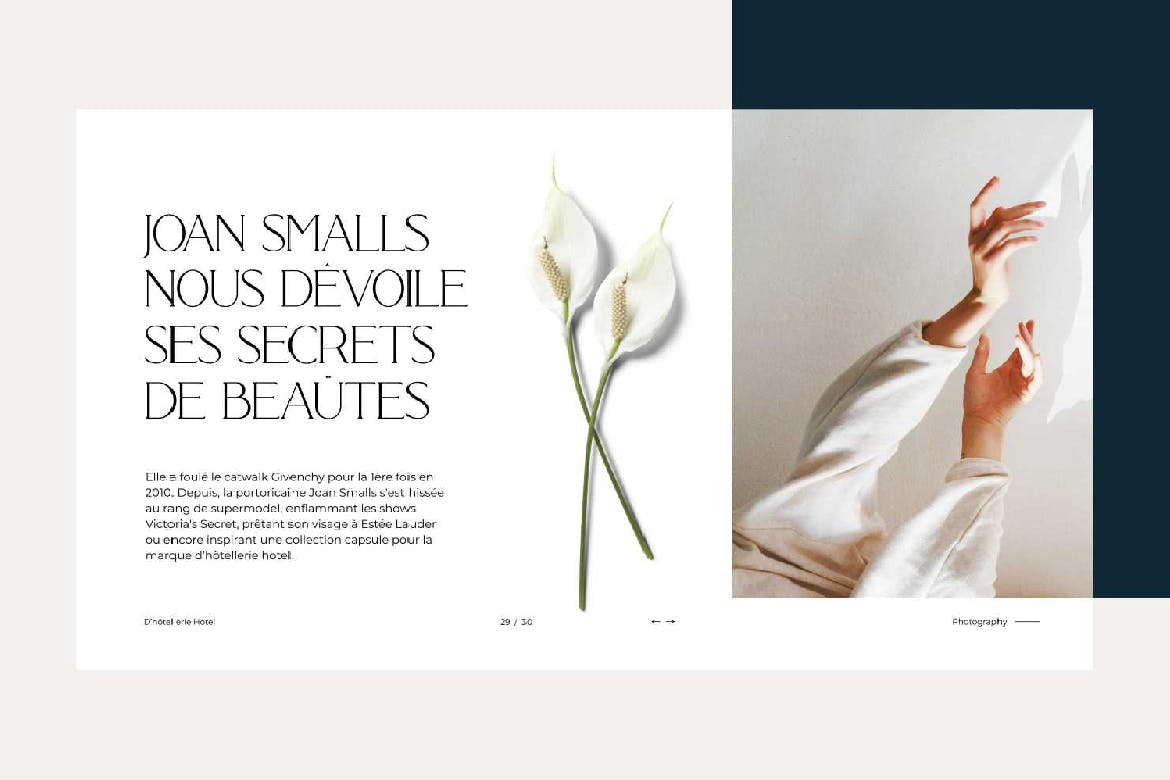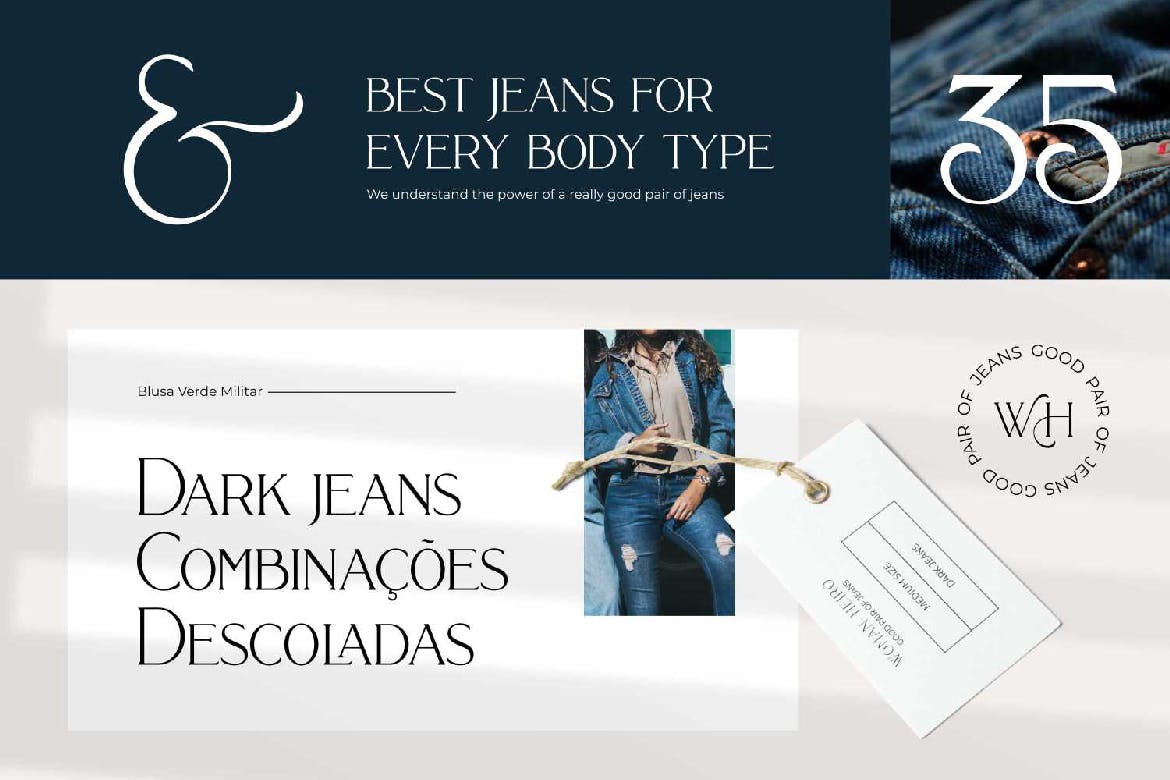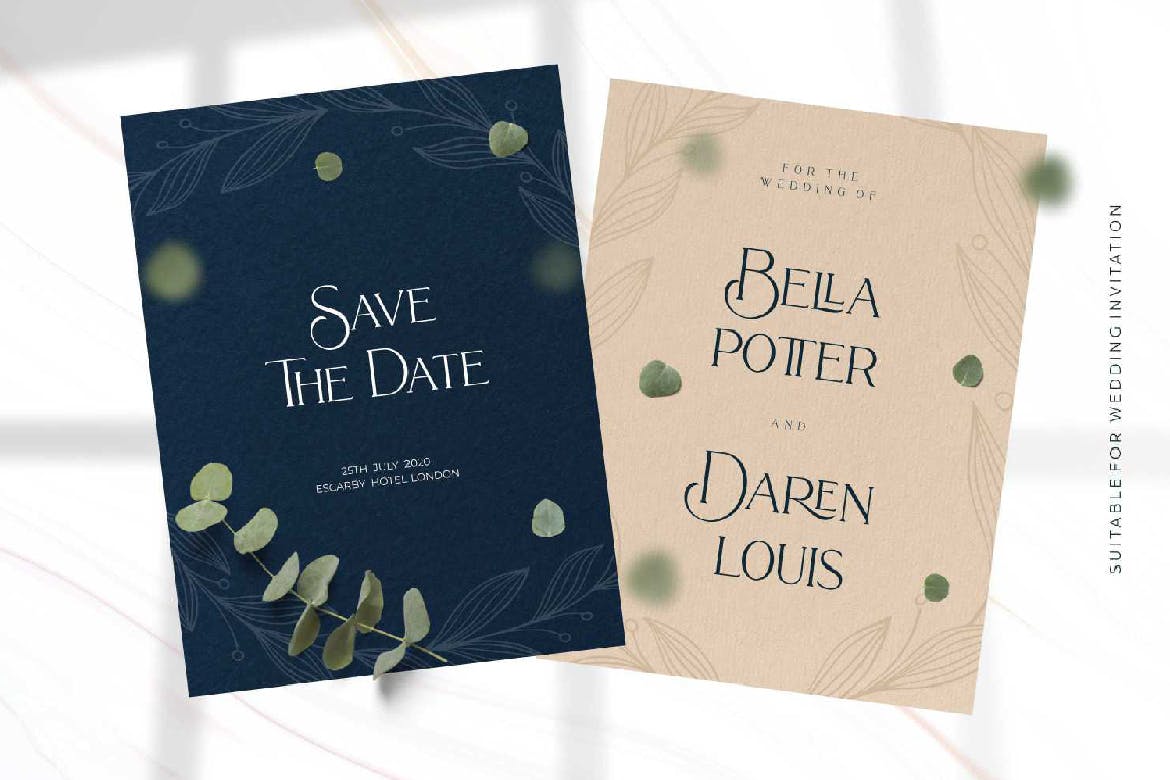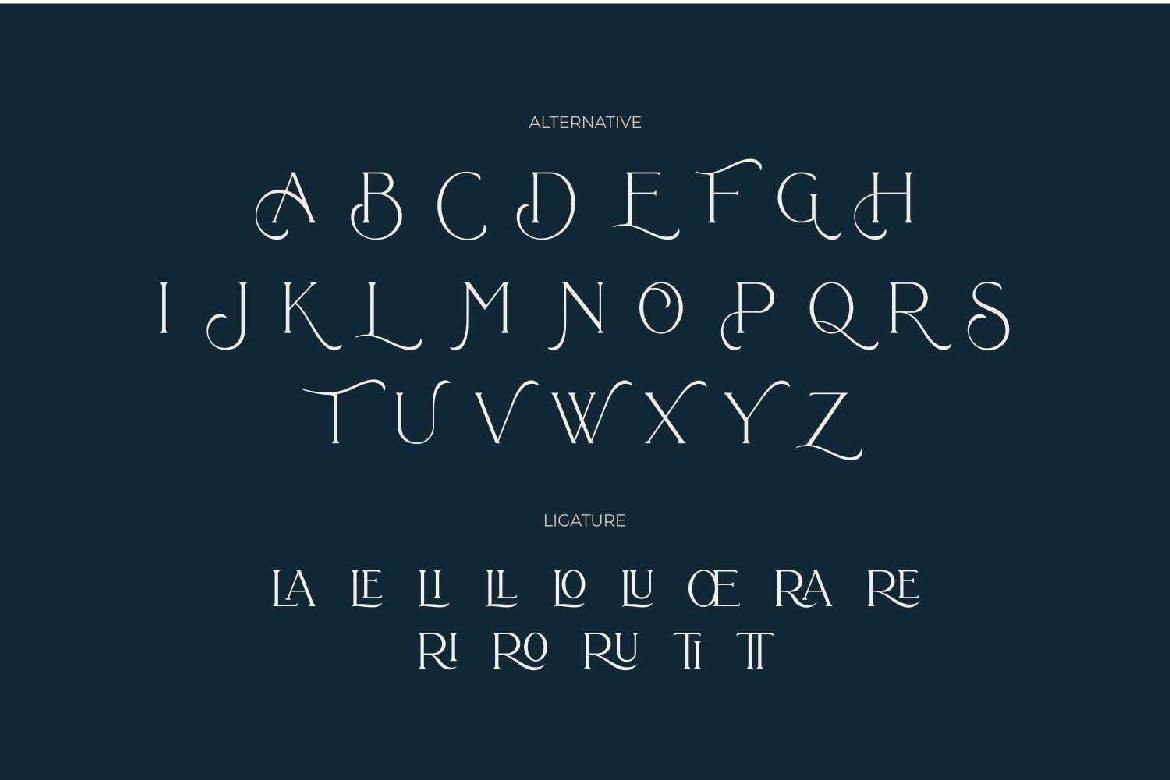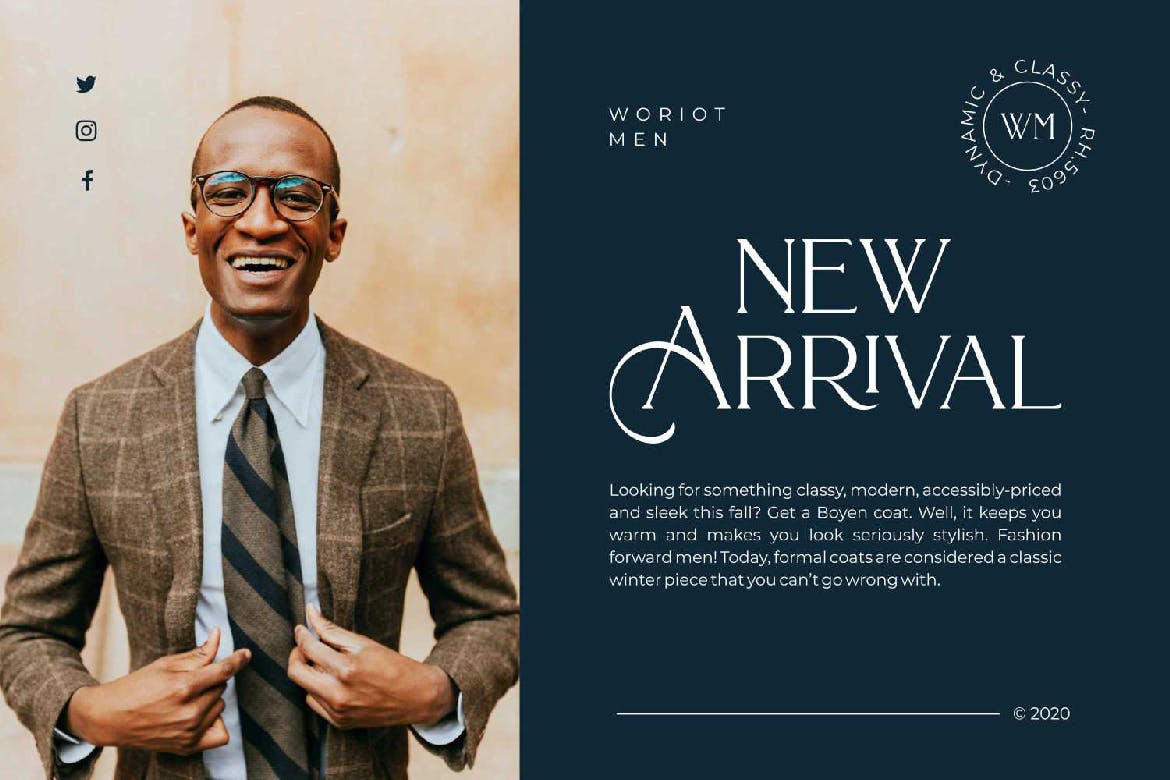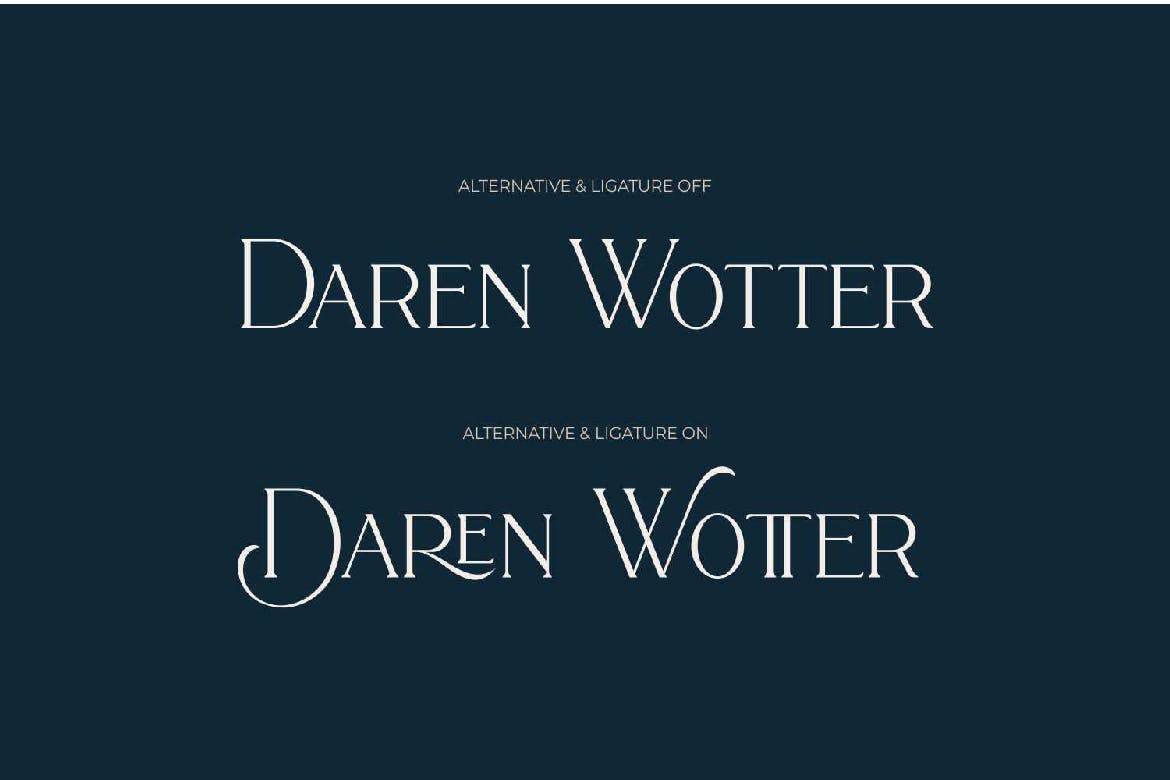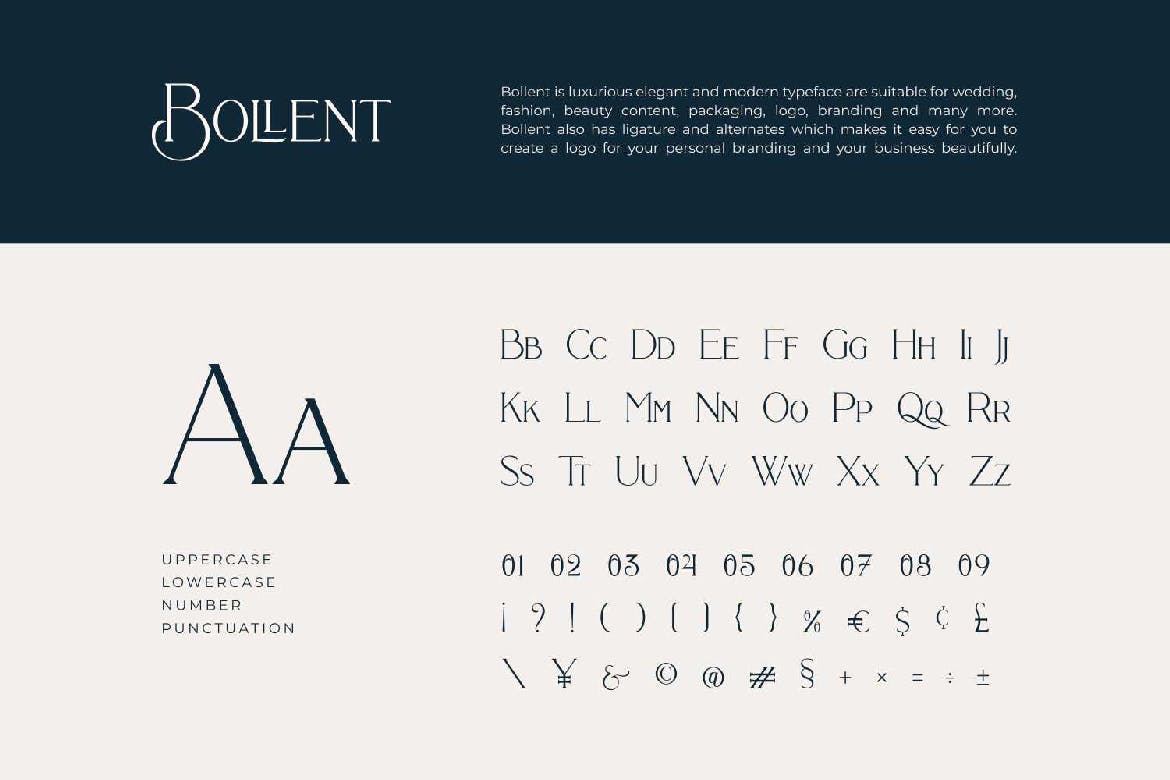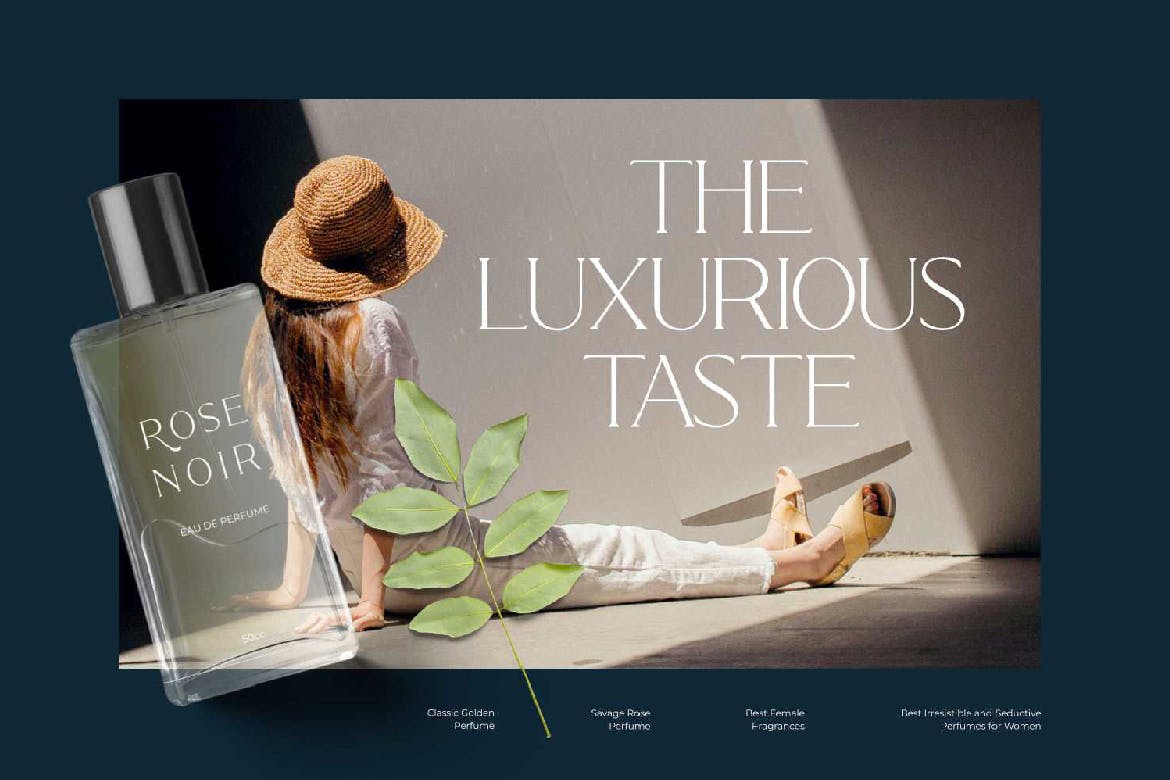
Modern Font Bollent
فونت Bollent با طراحی زیبا و مدرن، انتخابی عالی برای پروژه‌های شماست.
فونت Bollent یک نوع‌نگاره لوکس، شیک و مدرن است که برای طراحی‌های عروسی، مد، زیبایی، بسته‌بندی، لوگو و محتوای برندینگ بسیار مناسب می‌باشد. این فونت شامل لیگاتورها و جایگزین‌هایی است که به شما این امکان را می‌دهد تا لوگوی شخصی و کسب‌وکار خود را به شکلی زیبا طراحی کنید.
• طراحی شیک و مدرن
• مناسب برای پروژه‌های مختلف
• شامل لیگاتورها و جایگزین‌های متنوع